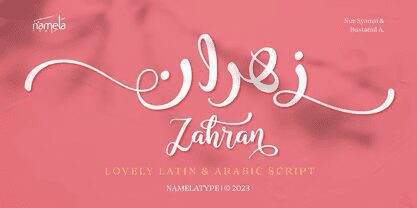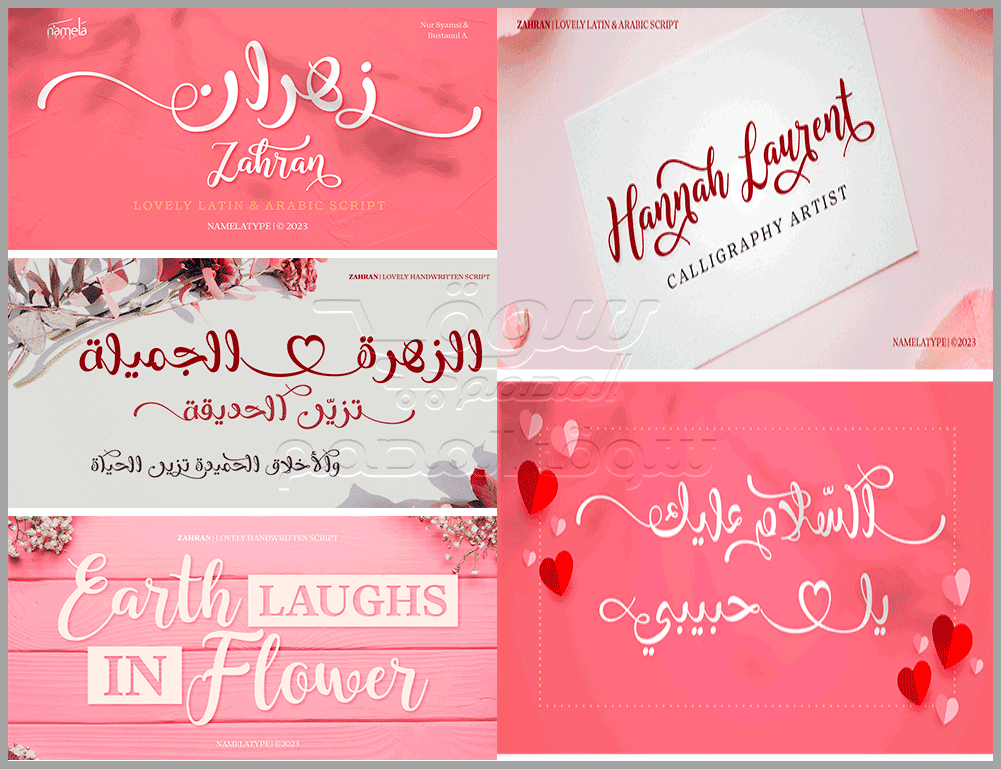
اكتشف الأناقة مع عائلة خطوط زهران. خط عصري متكامل يدعم اللغتين العربية واللاتينية بتناغم فائق، مثالي لتصاميم الشعارات والمواقع الإلكترونية والمطبوعات الفاخرة لعام 2026.
مراجعة عائلة خطوط Zahran Font Family
تعتبر عائلة خطوط Zahran (زهران) نموذجاً مثالياً للخطوط “الثنائية اللغة” (Bilingual) التي يزداد الطلب عليها في الأسواق العالمية. تم تصميم الخط ليحقق توازناً بصرياً دقيقاً بين الحرف العربي بانسيابيته والحرف اللاتيني بقوته الهندسية.
1. المميزات الفنية والتصميمية:
- التناغم البصري (Harmony): تم ضبط أحجام وأوزان الحروف العربية لتتطابق تماماً مع الحروف اللاتينية عند استخدامهما معاً في نفس السطر، مما يمنح التصميم مظهراً احترافياً وموحداً.
- التصميم العصري (Modern Sans-Serif Style): يبتعد الخط عن الزخرفة التقليدية الزائدة، ويميل إلى البساطة والوضوح، مما يجعله خطاً مثالياً للعناوين الرئيسية والفرعية.
- الأوزان المتعددة: تتوفر الحزمة بأوزان متنوعة (مثل Light, Regular, Bold) لتمنح المصمم مرونة كاملة في بناء التسلسل الهرمي للمعلومات داخل التصميم.
- سهولة القراءة (Readability): يتميز بمسافات بينية (Kerning) مدروسة بعناية، مما يضمن وضوح النصوص حتى في الأحجام الصغيرة أو على الشاشات ذات الدقة المتوسطة.
2. لماذا يحتاجه المصممون في عام 2026؟
- تصميم الهوية البصرية (Branding): الخط مثالي للشركات التي تستهدف جمهوراً محلياً ودولياً في نفس الوقت، حيث يحافظ على ثبات العلامة التجارية بلغات مختلفة.
- واجهات المستخدم (UI/UX): بفضل بساطته، يعتبر خياراً رائعاً لمصممي تطبيقات الجوال والمواقع الإلكترونية التي تتطلب لغة بصرية نظيفة ومريحة للعين.
- النشر الإعلاني: يبرز الخط بشكل قوي في تصاميم السوشيال ميديا والإعلانات الطرقية بفضل “سماكته” وتوازنه الهندسي.
- المشاريع الثقافية والتعليمية: يعطي طابعاً من الرقي والحداثة للمجلات والكتب المعاصرة.
3. نصائح فنية للاستخدام:
- العناوين الضخمة: استخدم الوزن Bold في العناوين الرئيسية مع إضافة مسافات بسيطة بين الحروف اللاتينية للحصول على مظهر “بريميوم”.
- التنسيق المشترك: عند كتابة جملة تحتوي على كلمات عربية وأخرى إنجليزية، لن تحتاج لتغيير حجم الخط أو نوعه يدوياً، حيث يقوم Zahran بموازنة ذلك تلقائياً.
- الخلفيات الملونة: يظهر الخط بوضوح عالٍ جداً عند استخدامه باللون الأبيض فوق الخلفيات الداكنة أو الصور المشبعة بالألوان.